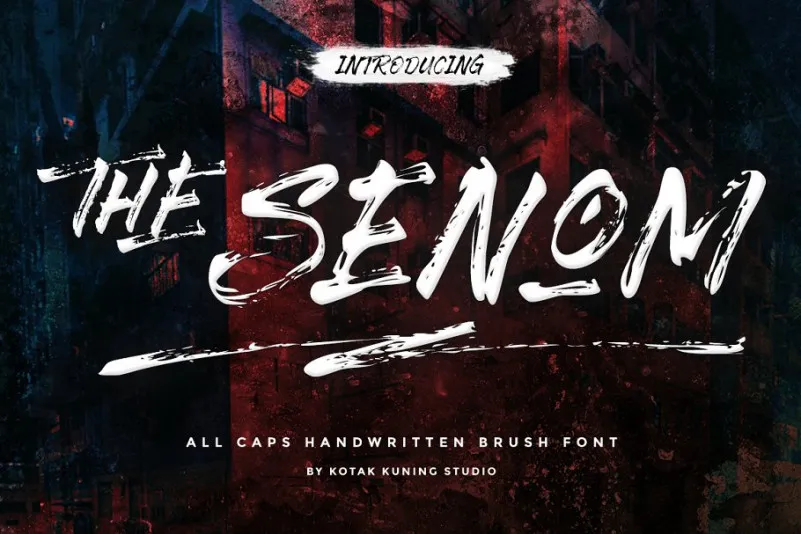
The Senom Brush Font – Download Grátis
Aqui está uma descrição em português para a página de download da fonte ‘The Senom Brush Font’, respeitando as instruções fornecidas: Venha explorar um novo amigo na sua biblioteca de recursos gráficos! Inspirado pela tipografia à mão, o The Senom Brush Font traz uma sensação vibrante e natural que pode transformar qualquer projeto em algo único e atraente. Desenvolvida pela Kotak Kuning Studio, essa fonte all-caps foi criada usando um pincel seco para dar vida aos seus designs. A ideia por trás dessa fonte é inspirada na arte à mão, que sempre teve uma conexão forte com o design gráfico. O The Senom Brush Font permite você criar texturas e formas vibrantes que podem destacar seu conteúdo sem perder a personalidade única do projeto. Ideal para aplicações de escrita criativa ou design editorial. E assim, se juntando à sua coleção de recursos digitais é um prazer verter o talento da Kotak Kuning Studio em suas criações! Inspirado na arte à mão clássica, o The Senom Brush Font oferece aos designers uma ferramenta poderosa para personalizar seus designs e torná-los ainda mais únicos. Não perca essa oportunidade de revolucionar a forma como você visualiza seu conteúdo! Agora é hora de experimentar o poder criativo do The Senom Brush Font – um aditivo autêntico que vai dar vida à sua próxima obra-prima!